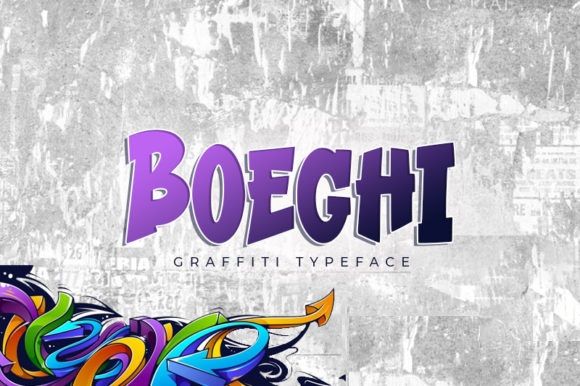
Boeghi
- это крутой, смелый и невероятно веселый шрифт.
Он воплощает игривость и аутентичность и идеально подходит для любых детских мероприятий или школьных проектов.
Добавьте этот шрифт с крупными буквами в свои проекты и заметите, как он оживит их!